草书是汉字字体里面的一种,结构非常简洁、笔画通常会连在一起。草书兴起与汉代,主要是目的是让书写更加简便,是在隶书的基础上演变而来的。分为章草、今草、狂草,狂乱而不失优美。接下来,字体视界小编为大家分析一下草书字体大全,草书的安装使用方法及特点有哪些,一起来看看吧。
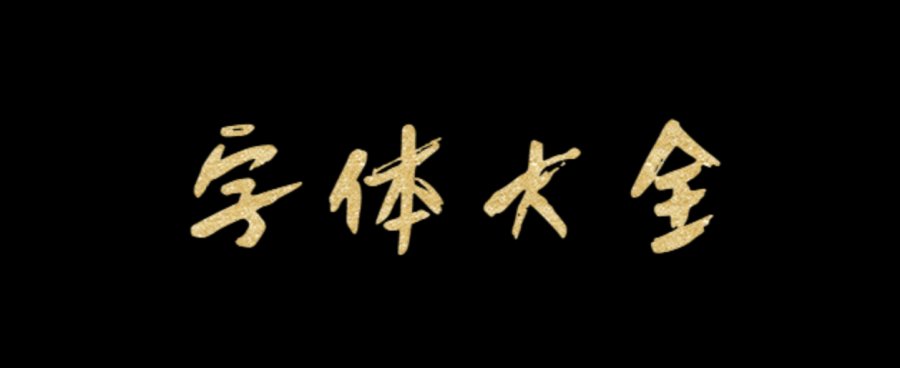
2、草书的特点
草书字体转换器是非常实用的,里面收录了十款草书字体,在列表转里面大家一目了然。草书字体包汇集了字体视界精心挑选出来的、好看的草书字体,其特点就是结构非常简单明了、畅快,表面看起来很狂乱,但是又可以让人感觉到其优美和强大魅力,各种不同风格和特点的草书字体,大家可以根据自己的实际需要选择下载使用。